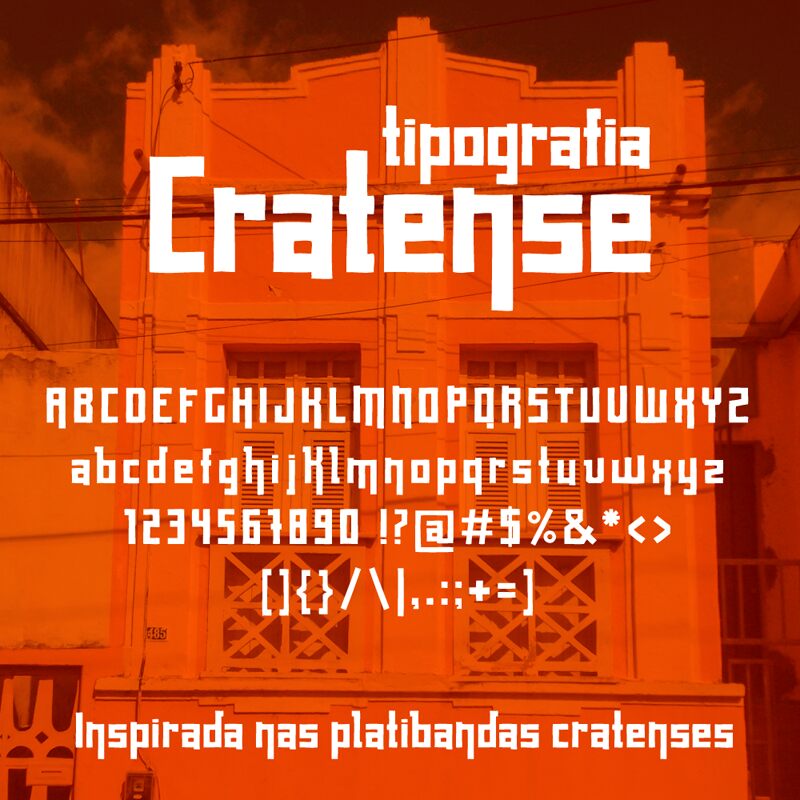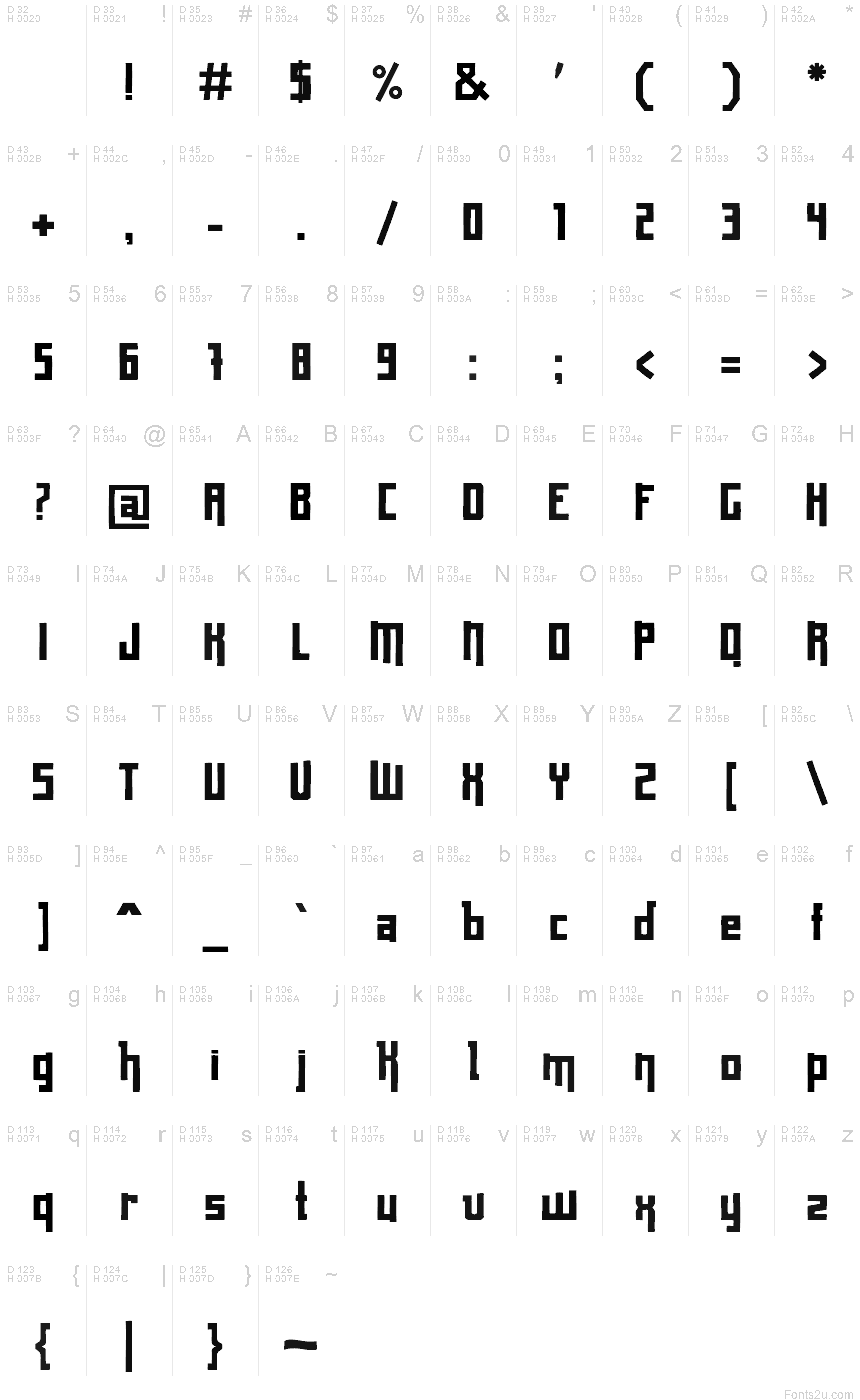
Cratense
Com intuito de preservar e promover a memria histrica do Crato, a tipografia "Cratense" foi inspirada na arquitetura nordestina e desenvolvida a partir do registro fotogrfico das platibandas do Centro da cidade. As platibandas ainda so muito frequentes na cidade e deixaram como forma de expresso artstica dos mestres pedreiros marcas nicas e se tornaram identidade das pequenas cidades. Por ser display um tipo ideal para ttulos e textos curtos.